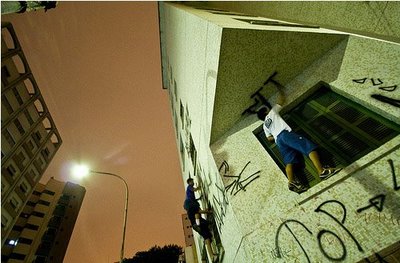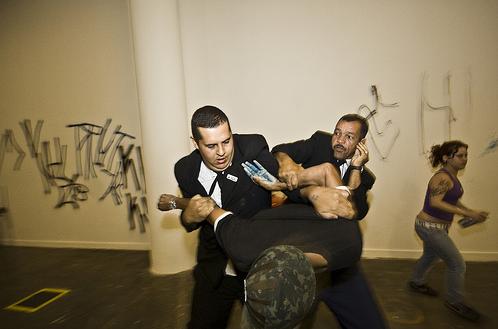
El pixação (pishasao)es un estilo de graffiti callejero y marginal que se da en Brasil desde la década del '60 hasta la actualidad. Se trata básicamente de escribir el nombre del artista o de su crew (pandilla) en el lugar más inaccesible y alto posible para, de ese modo, ganar prestigio por sobre los demás pixadores. Por esto, no pocos han muerto al caer al vacío desde cornisas de edificios y puentes.
Los signos remiten a runas y son realizados con trazos rápidos que tienden a la verticalidad.
Las herramientas más comunes son el aerosol, rodillos, brochas, marcadores o elementos fabricados de manera casera.
El pixação está penado por la ley y es sumamente perseguido en la actualidad dado la magnitud a la que ha llegado, sobre todo en San Pablo. Se dice que un pixador detenido debe comerse el pico de su lata porque de lo contrario la policía le pinta la cara usando el aerosol incautado.
Pixação al ataque
La Bienal de Arte de San Pablo de 2008, dedicada al arte conceptual -en la cual hubo una sala completamente vacía y pintada de blanco- fue "atacada" por varios pixadores que escribieron las paredes. Luego, escaparon forcejeando con el personal de seguridad del evento, quedando detenida una pixadora.